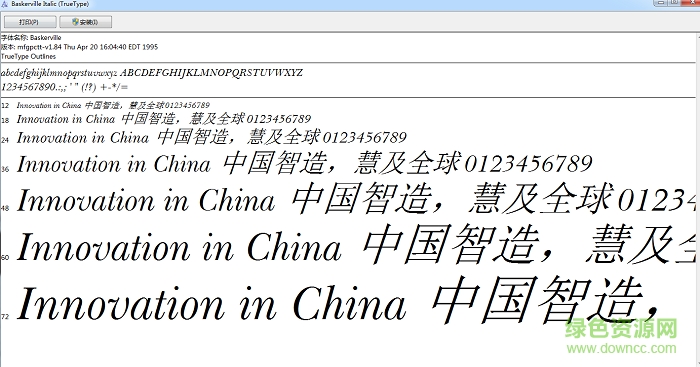
baskerville italic bt字體是一款非常耐看的英文斜體字體,纖細(xì)優(yōu)雅不失浪漫,該字體廣泛應(yīng)用于書刊、雜志等各個(gè)方面,需要的朋友快來(lái)下載吧!
1.表示引用
2.外語(yǔ),如英文文章中夾雜的法語(yǔ)
3.表示強(qiáng)調(diào),喚起注意
4.書籍名稱、文章標(biāo)題、船舶名稱等